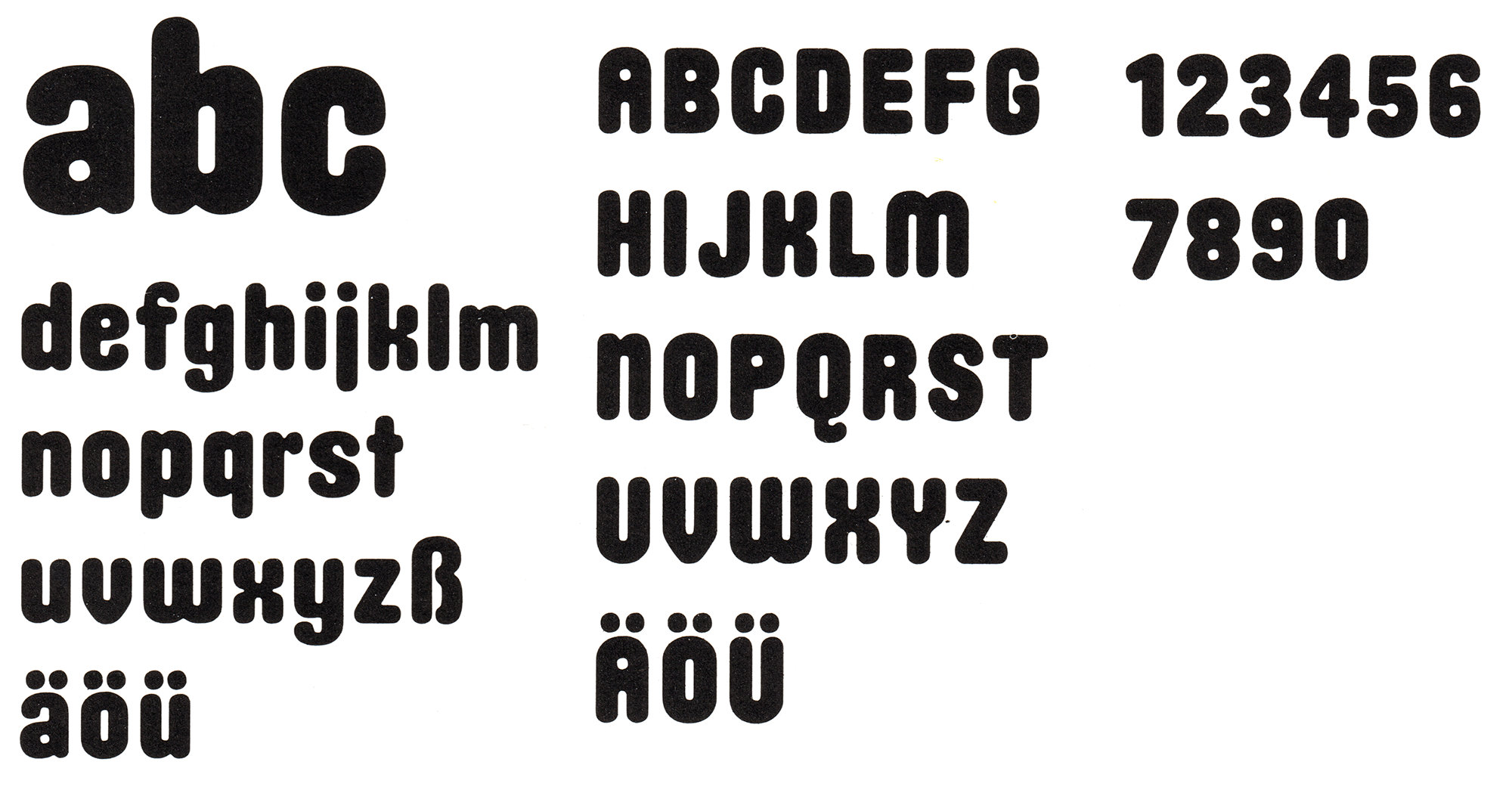
Font-Wiki: Molli
• circa 1989
• Antiqua dekorativ
Die Molli ist eine abgerundete Groteskschrift von Harald Brödel und erschien in den 1980er-Jahren als Fotosatzschrift beim VEB Typoart. Laut Anbieter sollte die Schrift eine »liebenswerte Ergänzung zu dem überwiegend von klassischen Formen geprägten Schriftprogramm empfunden werden«.
Elsner+Flake hat eine digitale Version auf Basis der Originaldaten aufgelegt.